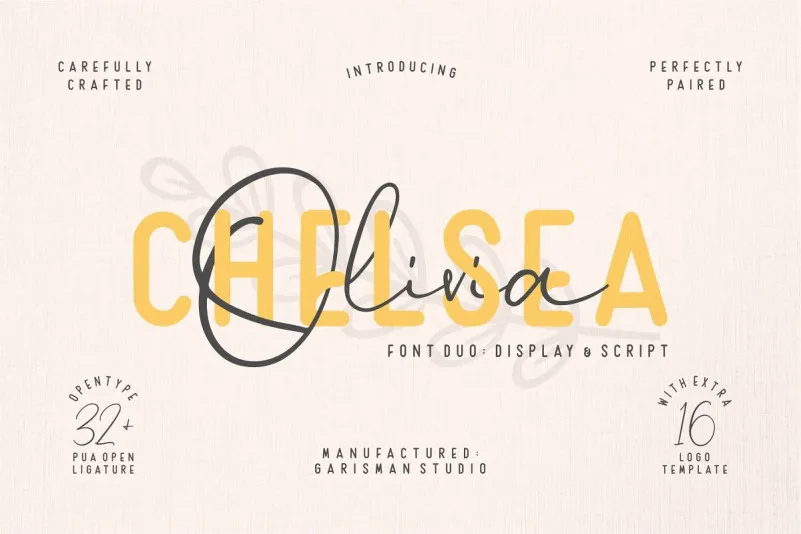
Chelsea Olivia Font Duo – Download Grátis
Esta é uma fonte agradável e simples, com sabor elegante, que vem com variações para letra script e tipo sans serif (todas as letras maiúsculas). Ela inclui recursos do OTP como ligaturas. Esta dupla de fonts é perfeita para fotografia e muitos outros projetos de design. Introduzimos Chelsea Olivia Font Duo. O designer é Garisman Std, apresentando um duo quente e rica em ligaturas! Este super-parecido é perfeito para logotipos (incluindo 16 logomarcas prontas e que você pode editar novamente), convites de casamento, aniversários, cartazes, postais empresariais, logos, subtítulos, Stories no Instagram e YouTube, capas de livros, promoção de posters e muito mais! Adquira a melhor combinação de fonts com Chelsea Olivia.